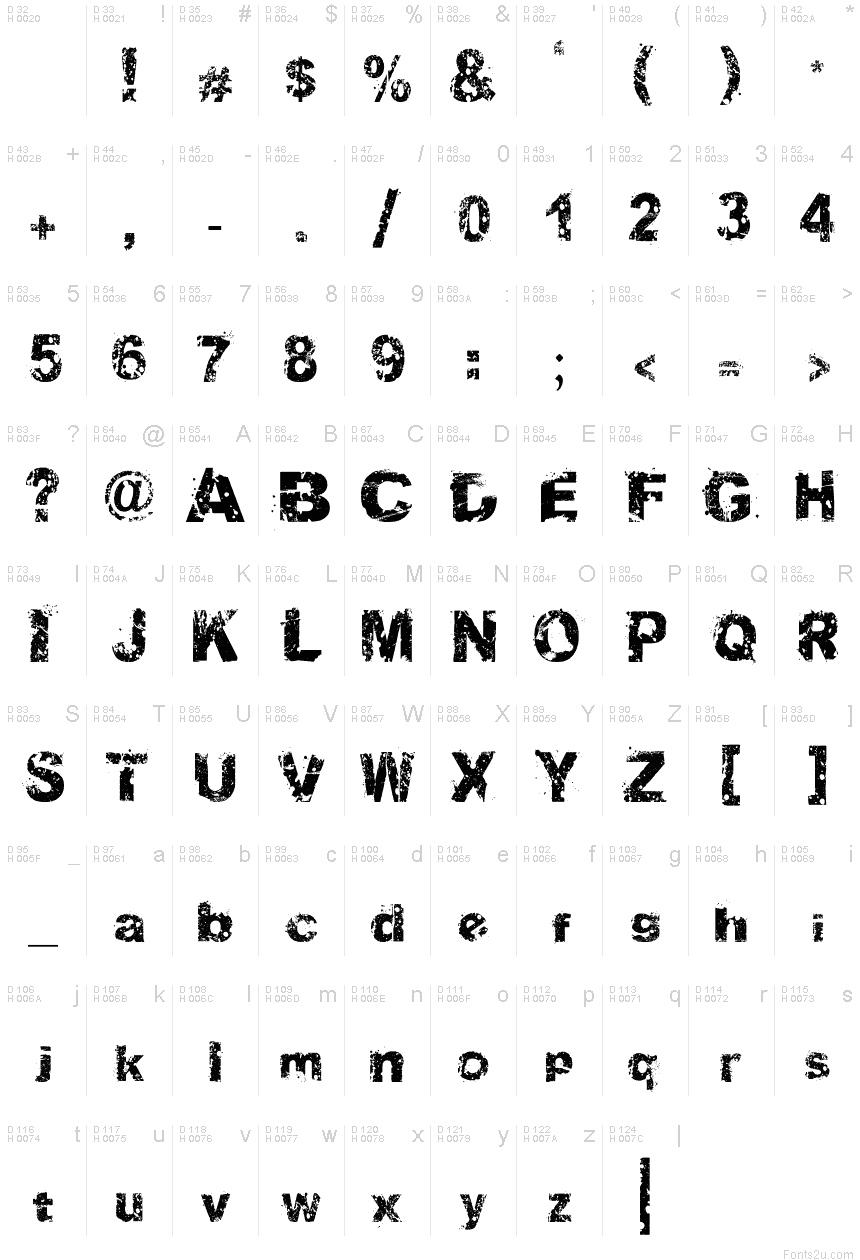
Soul Mission autorstwa RoCU to darmowy, wyrazisty krój displayowy o surowym, grunge’owym charakterze, przypominającym powierzchnie zdrapane, zachlapane i zużyte. Litery są masywne i czytelne, ale ich krawędzie rozpadają się na drobne plamki i ubytki, co nadaje całości klimat postarzanego druku ulicznego, a nie sterylnego, cyfrowego wykończenia.
Dzięki temu ten darmowy font jest naturalnym wyborem do nagłówków na plakatach, okładek płyt, grafik w stylu skate i streetwear, ulotek czy napisów, gdzie to właśnie zniszczona tekstura robi największe wrażenie. Świetnie sprawdza się także w krótkich hasłach brandingowych czy wyróżnionych cytatach, ponieważ solidne formy liter przekazują konkretny komunikat, a efekt erozji dodaje mu pazura.